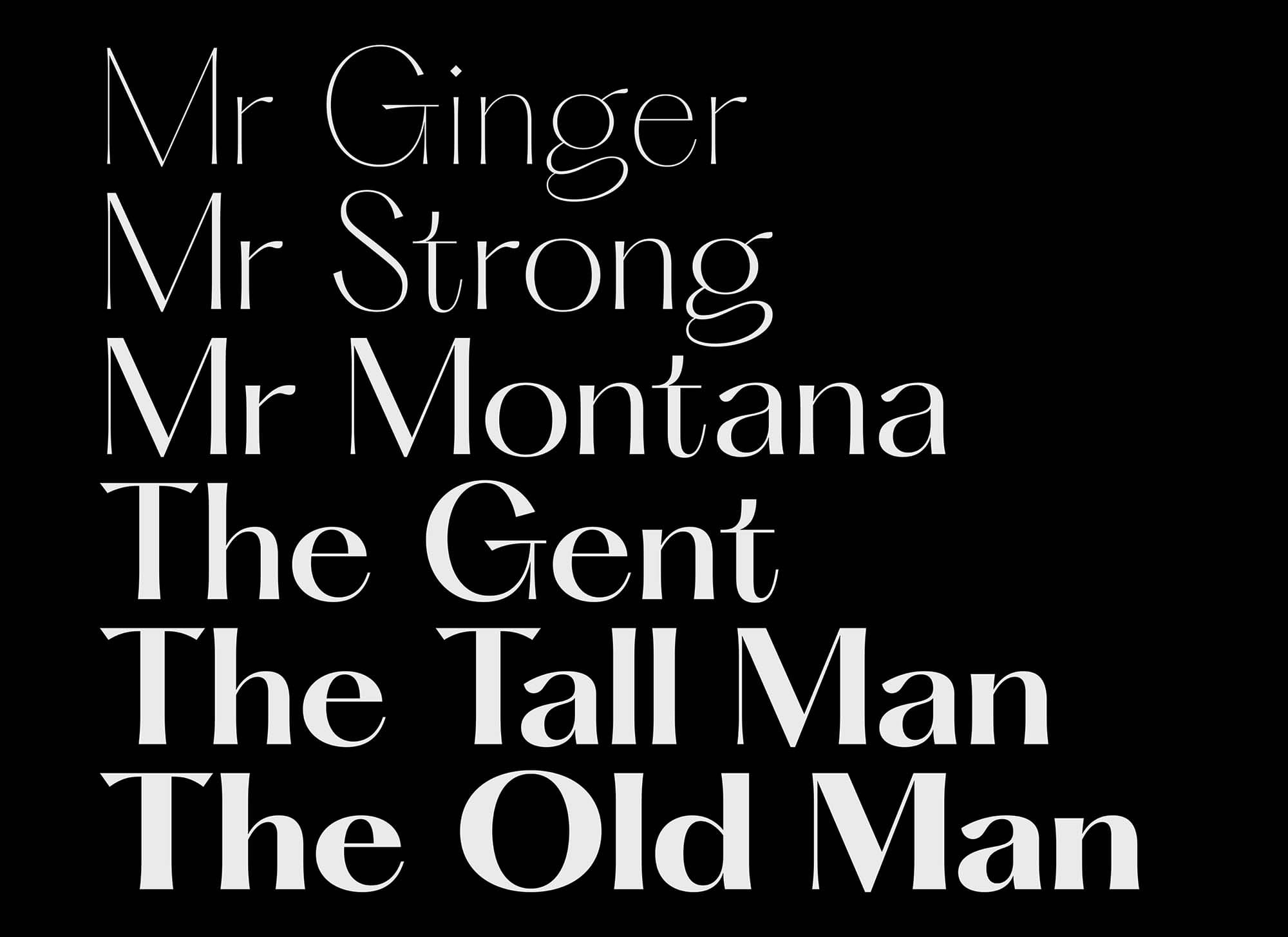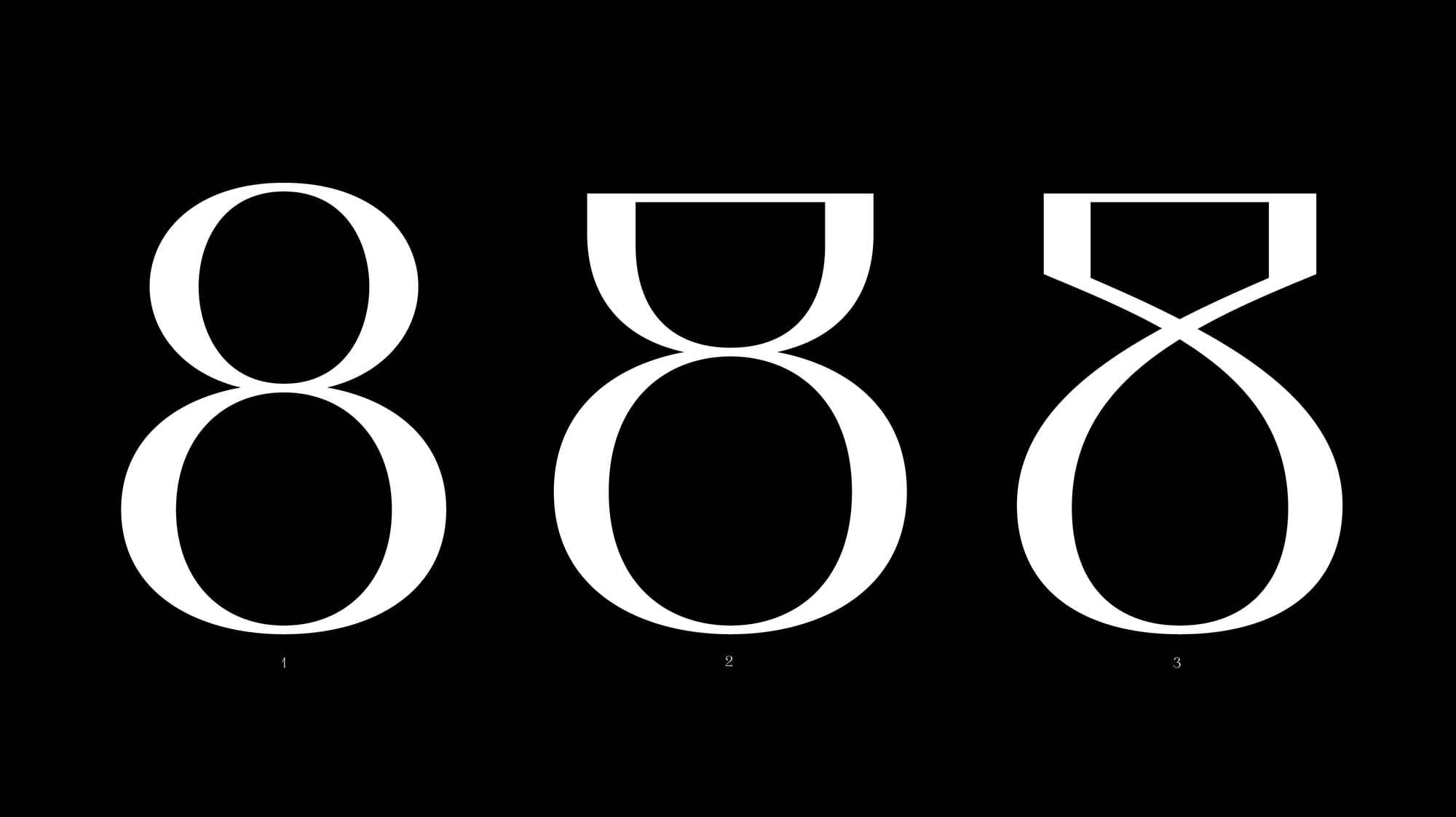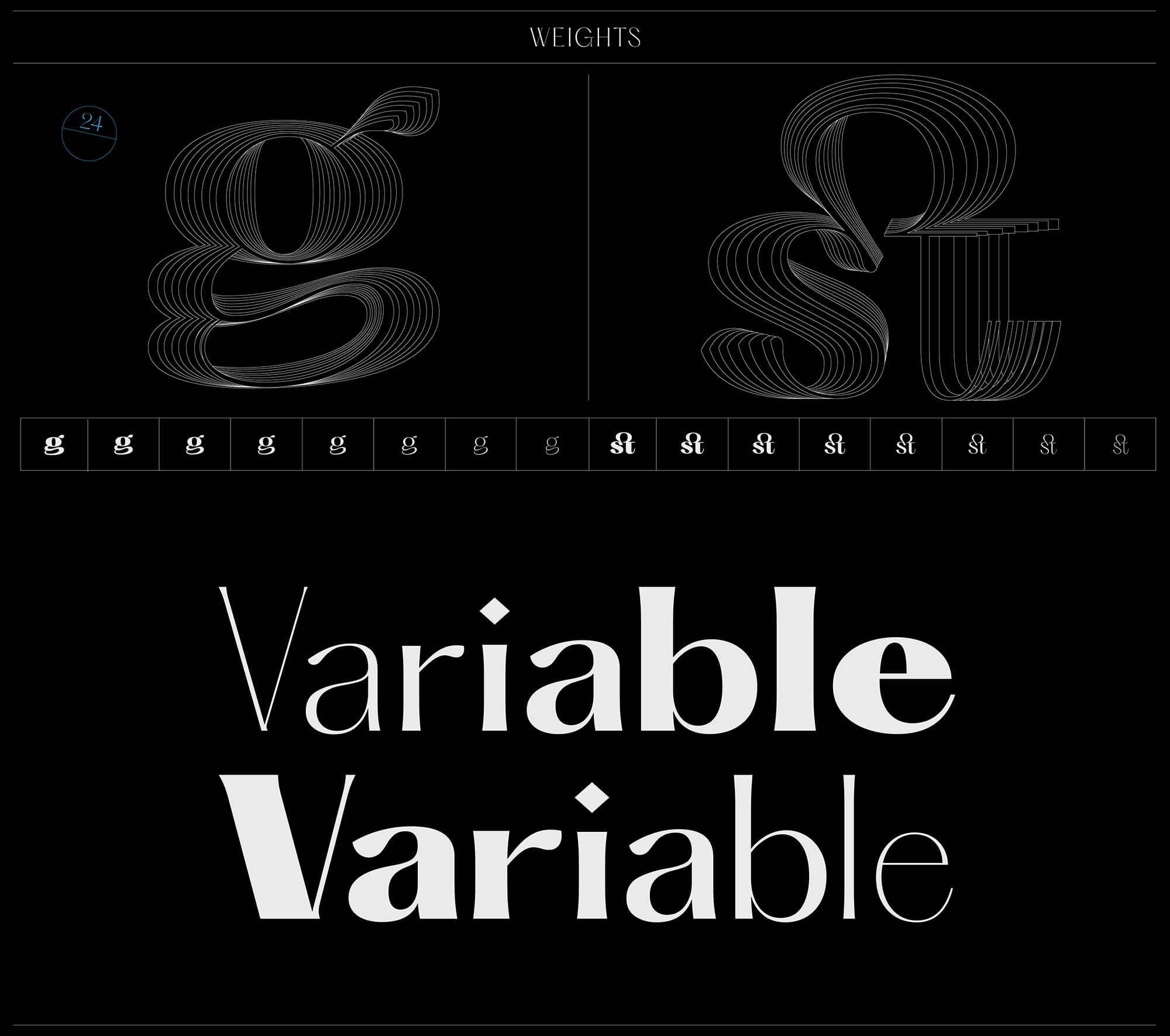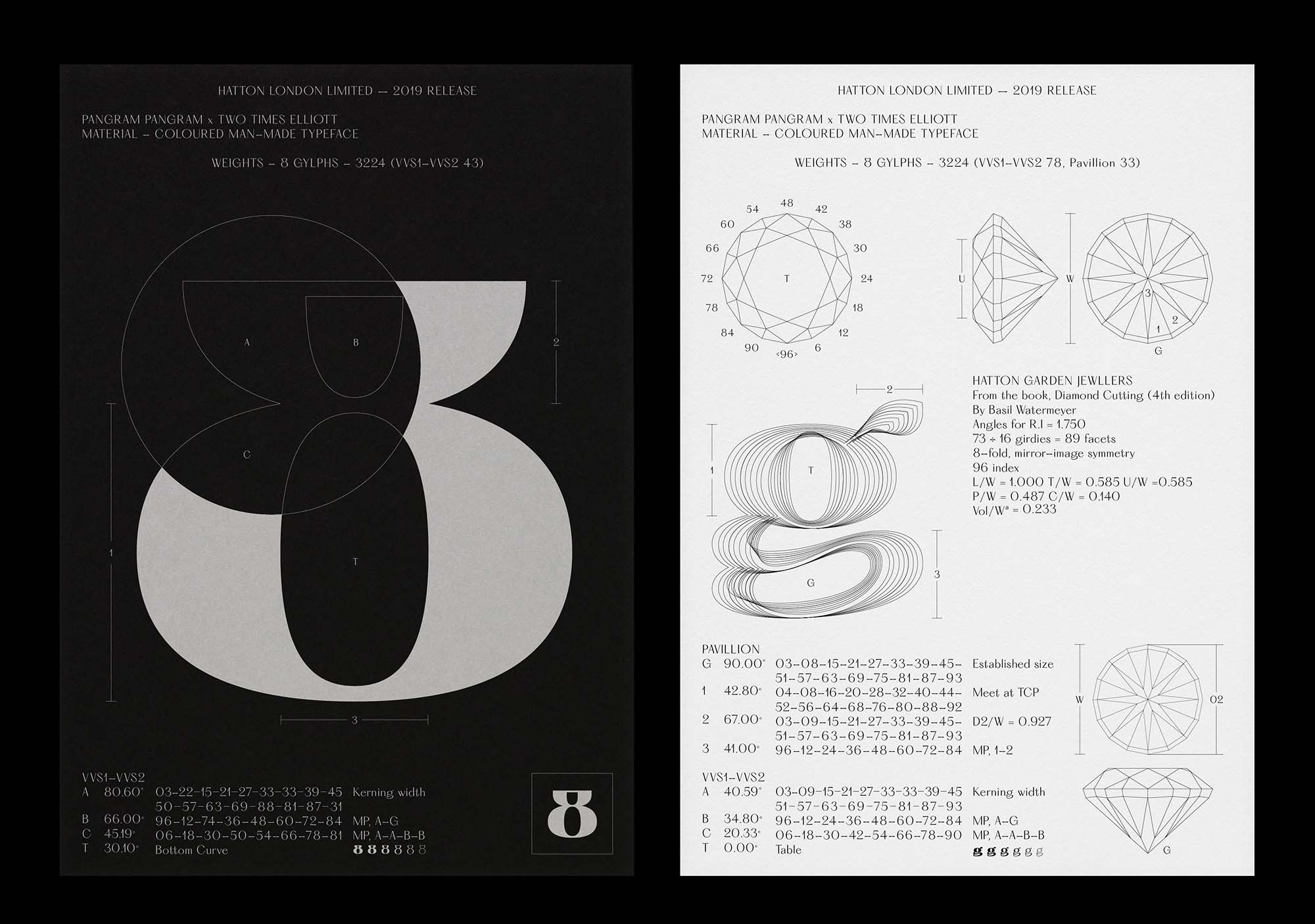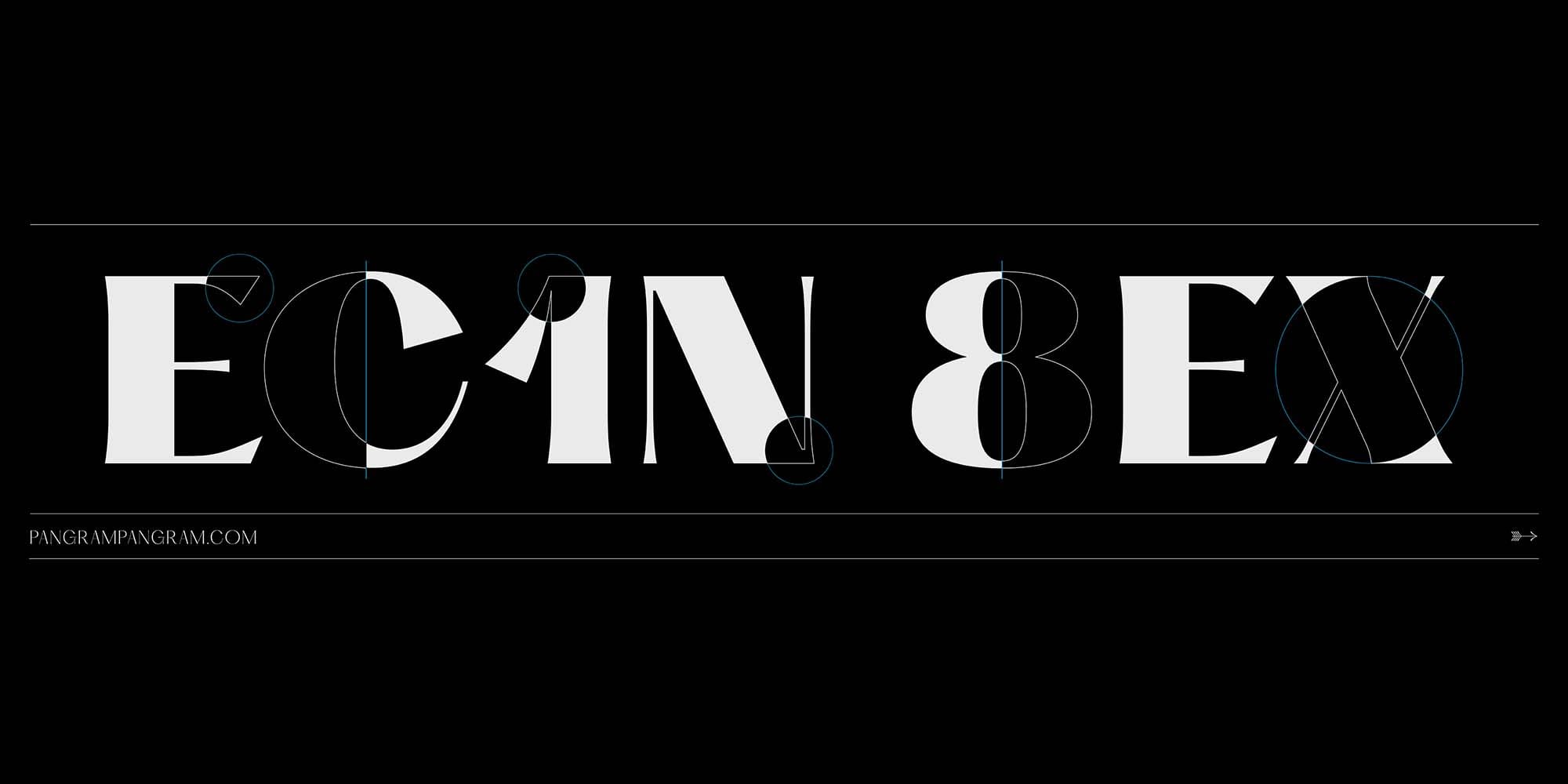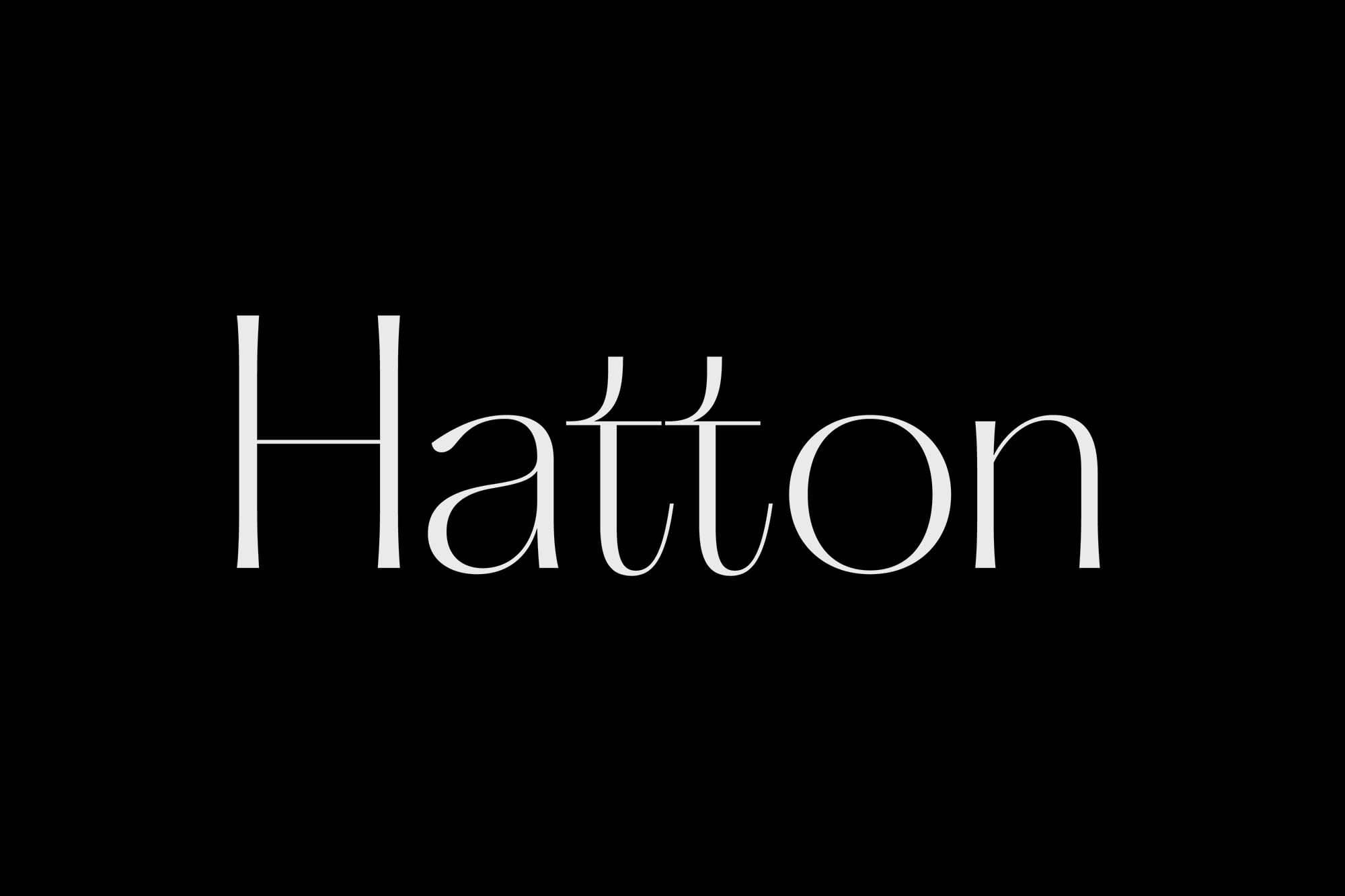
Được thiết kế dưới sự hợp tác với studio thiết kế Two Times Elliott có trụ sở tại London, Hatton là một font chữ thiết kế dựa trên lịch sử của quận Hatton, London. Nép mình trong ngôi nhà cũ của studio thiết kế, Clerkenwell, Hatton Garden nổi tiếng là khu phố trang sức ở London và là trung tâm của hoạt động buôn bán kim cương ở Anh. Các studio đã làm việc cùng nhau để chắt lọc đặc điểm và sắc thái của biển báo địa phương, biển hiệu, mặt tiền cửa hàng và các địa danh chỉ có ở vị trí Hatton Garden, đồng thời ghi lại sự không hoàn hảo và bản chất vẽ tay của chữ được tìm thấy.Kết quả là một kiểu chữ mang phong cách riêng thể hiện lịch sử nghề thủ công trong khu vực thông qua một tập hợp các ký tự, chữ ghép và nét chữ độc đáo. 8 kiểu với 403 glyph mỗi kiểu.